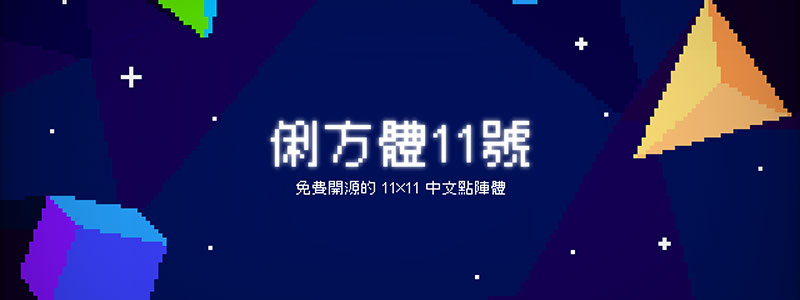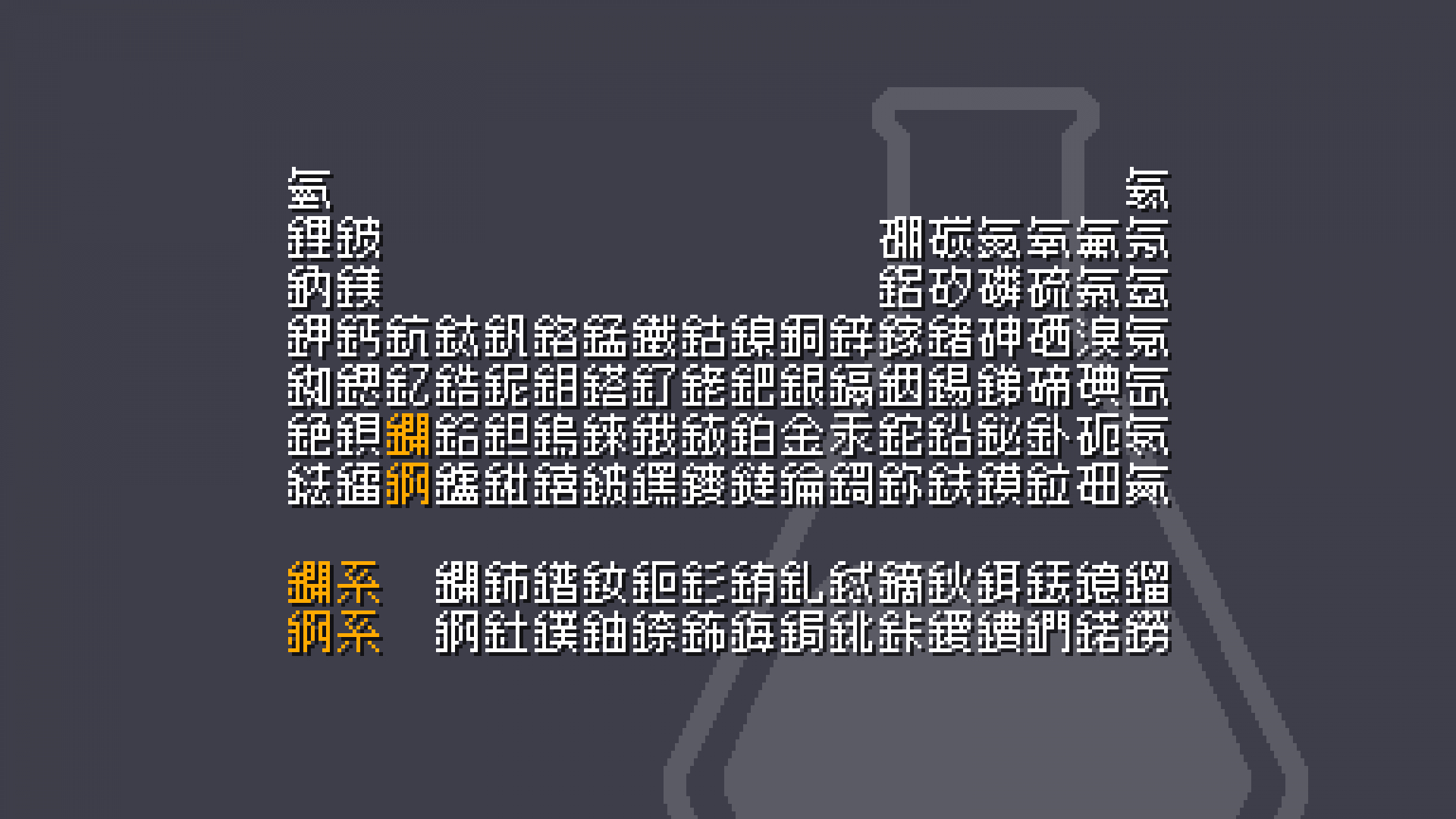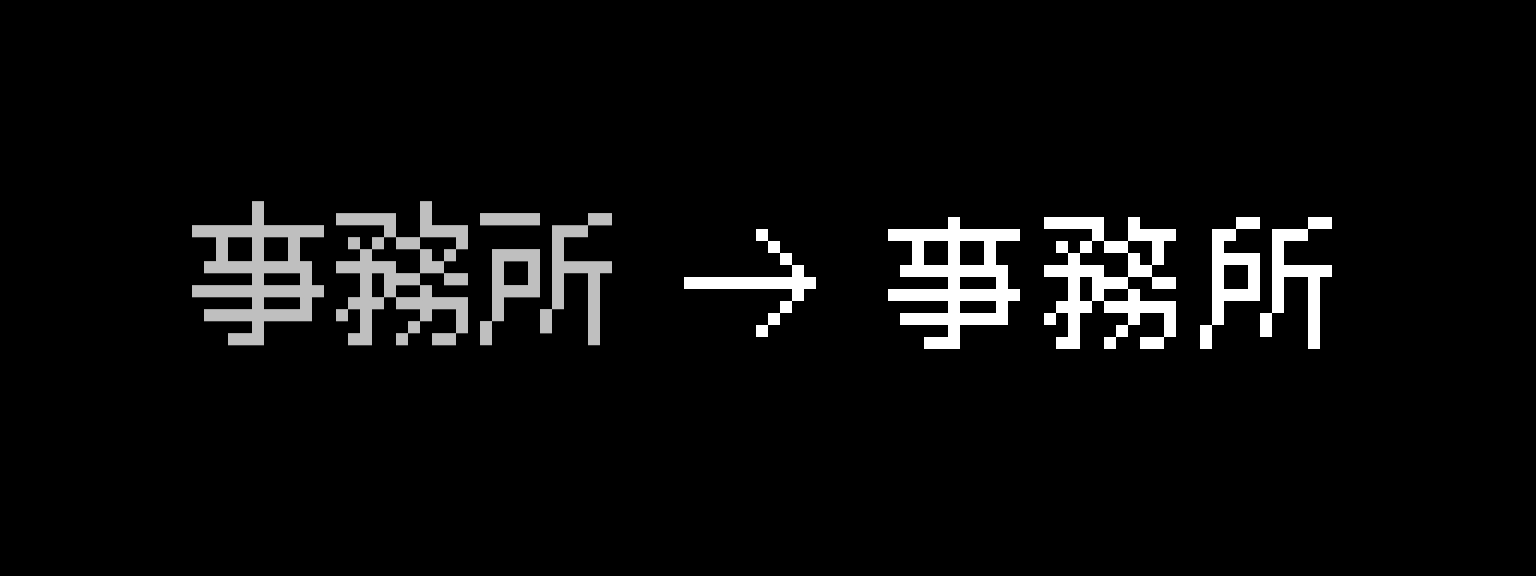
俐方體11是基於M⁺goic 12r衍生的開源繁體中文11×11點陣字體,可用於創意風格的遊戲以及算法原型。
收錄字數:常用國字標準字體 4808 字;Big5第一字面5401;IICore 臺灣常用字 T1A、T2A 及部分 T2B;臺客閩粵字;注音符號;GB 2312 Level-1;通用規範漢字表 一級;元素週期表之所有元素符號。
本字型以日文字型 M⁺ gothic 12r 為基礎替繁體中文進行修改與擴充,其中包括適用繁體中文的標點符號以及較符合臺灣地區習慣的字形等。